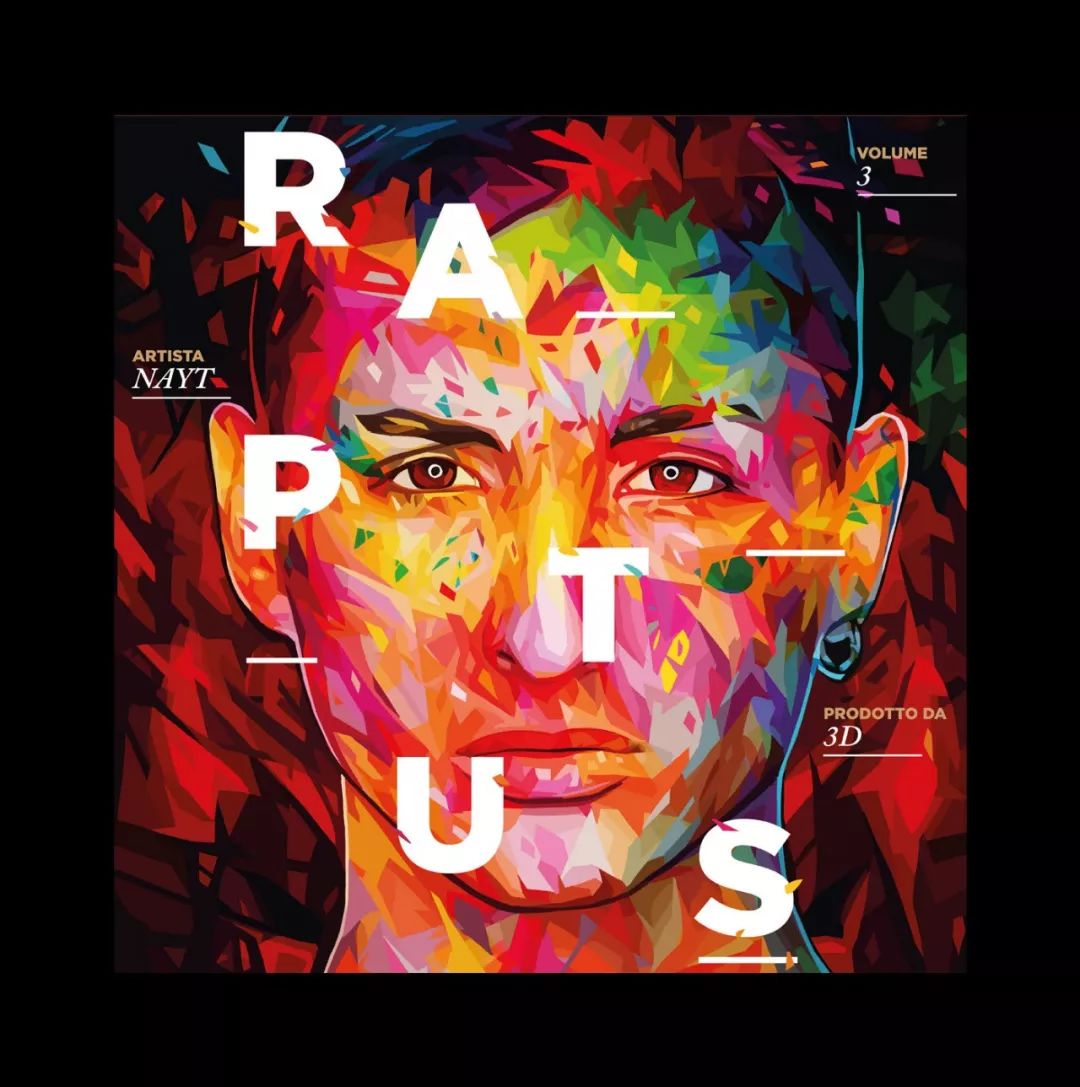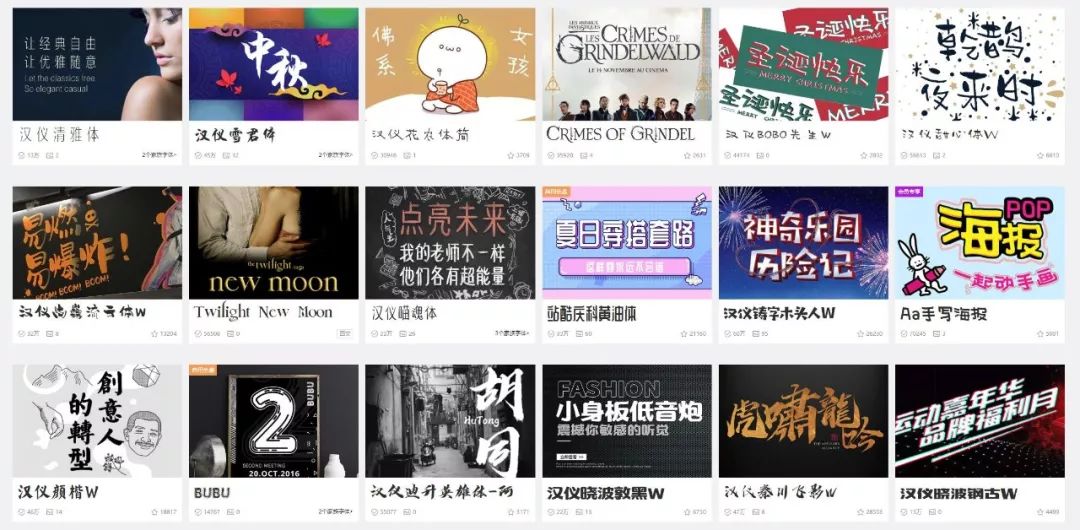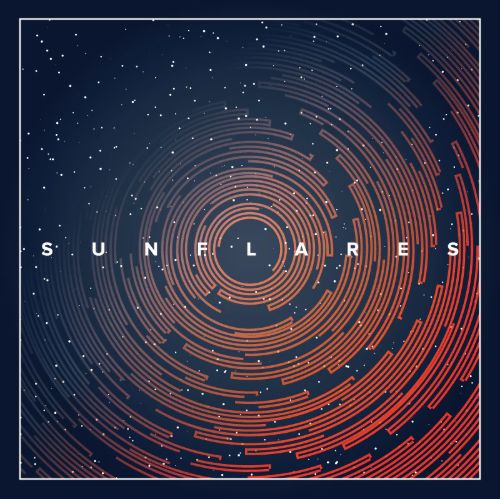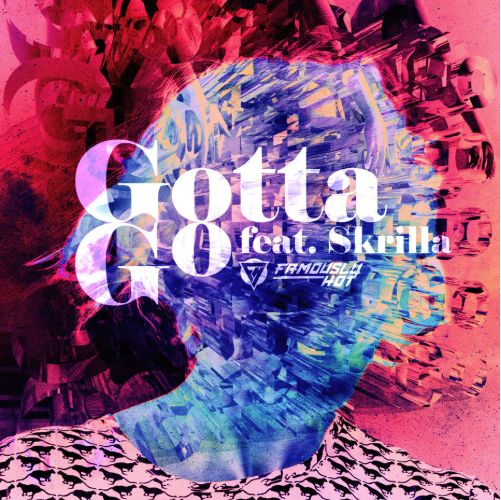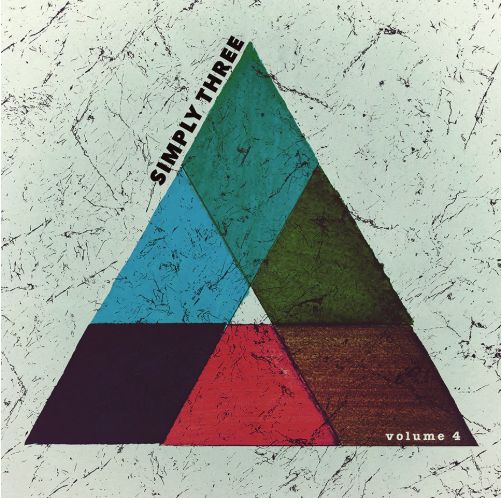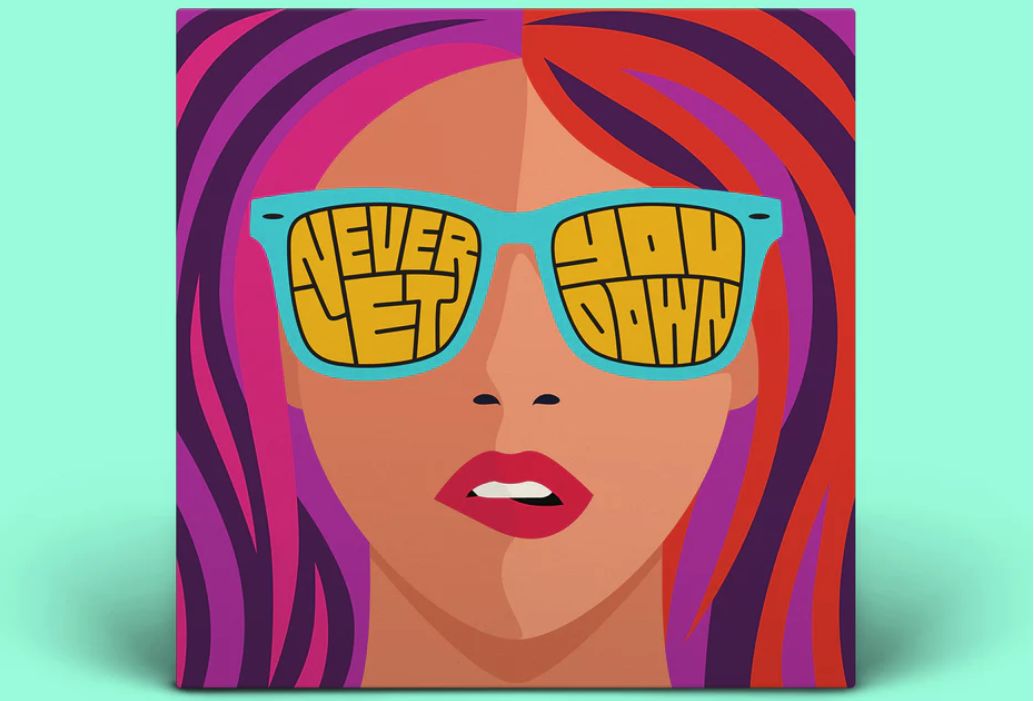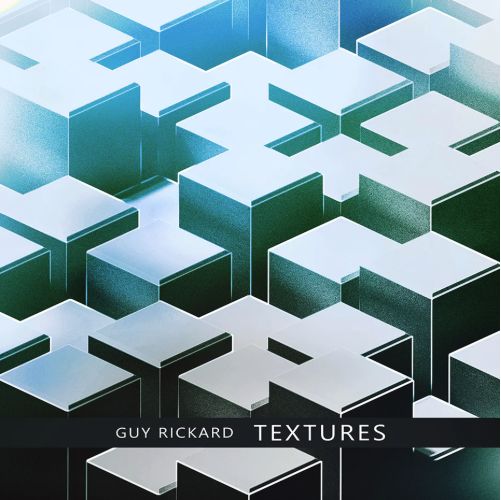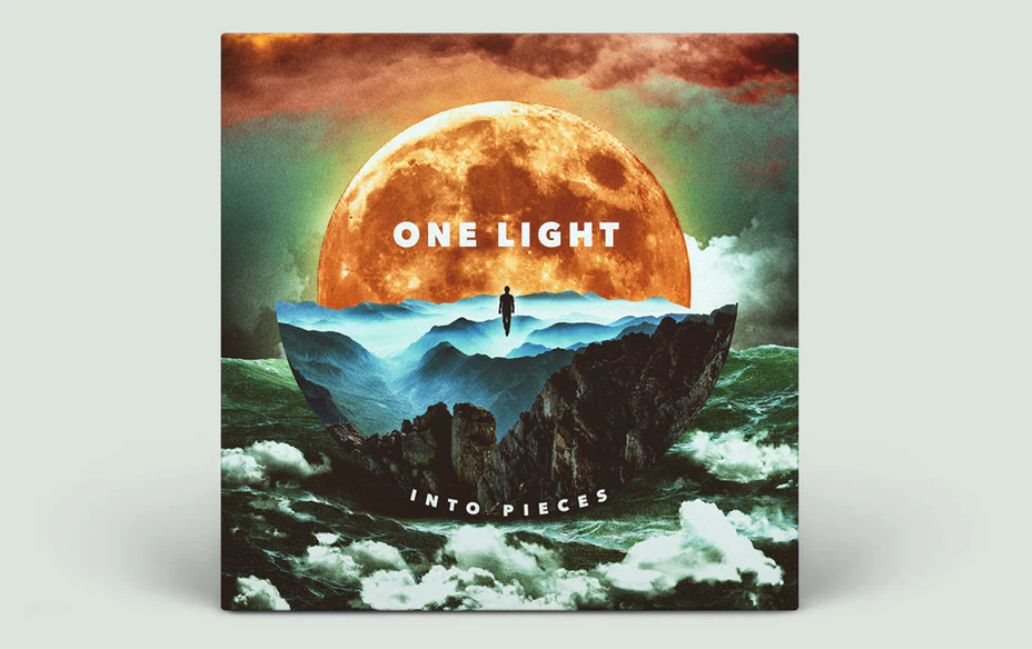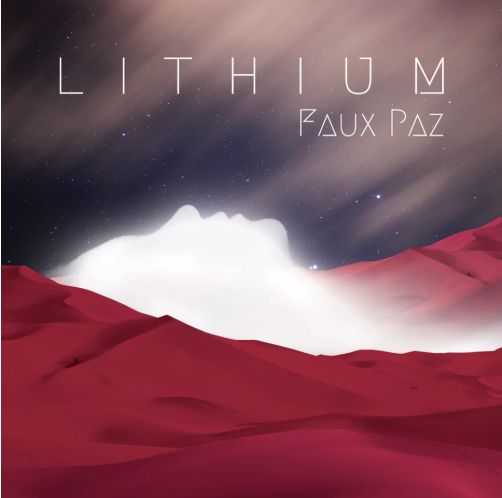
如何做好一个封面?教你从音乐专辑里找灵感~
昨天说完了标题字,今天来说说封面,它就像一张名片,承载着别人对你的第一印象,字由官网上的字体封面图,就各有其气质~
让人很想点进去,了解字体,如果没有这一步,字体就是黑白的存在。
音乐更是如此,虽然现在都是戴上耳机,就能享受片刻的“抽离”,但经典的专辑,一定离不开有设计感的封面,今天我们就来看看。
几何元素
这个概念是现代专辑封面的坚实方法。你不需要大量的人和文字,就能把你的内在表现出来。
大胆撞色
人人都容易被亮眼的视觉吸引,专辑也不例外,把字体嵌入在封面中最为巧妙~
超现实未来
当音乐无法归于某一流派,这种风格最适用,因为能带给人无限的想象力……
调色板